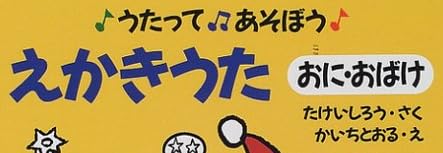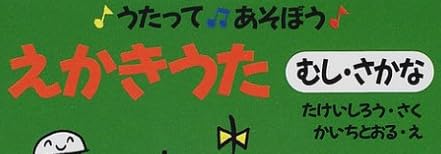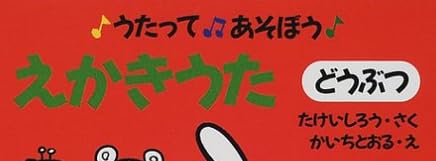
児童書『ちいさなミリー』 シリーズ の ゴカール
※他のゴカールの「と」
「ミ」の一角目のくねりが消されていたり、
「リ」も一角目の角度が違うような気がします。
※他のゴカールの「ミ」「リ」
「と」が違う
「と」が他のゴカールの「と」と異なる様子です。※他のゴカールの「と」
「ぐりとぐらかるた」の「と」
「ずーっとずっとだいすきだよ」の「と」
「ミリ」も違う
あと、「ミ」の一角目のくねりが消されていたり、
「リ」も一角目の角度が違うような気がします。
※他のゴカールの「ミ」「リ」
「ハッピーファミリー」の「ミリー」
ゴカールですが、「の」の突き出しを引っ込められているようです
参考
普通のゴカールの「の」と思われる「の」
楽譜『うたってあそぼう えかきうたシリーズ』
「どうぶつ」の「ど」、「かいちとおる」の「と」は、
突き出しを削られているのだと思われます。
ゴーカルの「と」は突き出すのだと思うので…
「どうぶつ」の「ど」、「かいちとおる」の「と」は、
突き出しを削られているのだと思われます。
ゴーカルの「と」は突き出すのだと思うので…
参考
普通のゴカールの「と」はこうです。